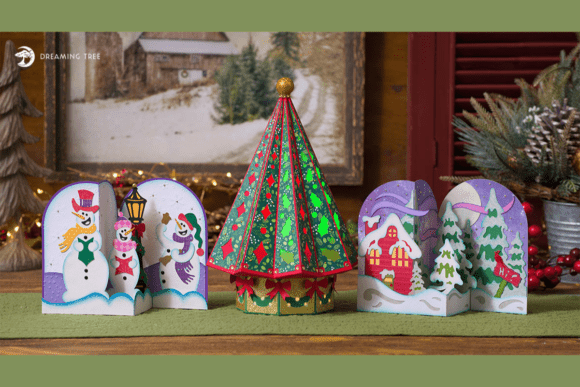
Early Bird Christmas SVG Bundle
Encontrar los elementos de diseño adecuados puede ser un desafío, pero Early Bird Christmas SVG Bundle ofrece una colección excepcional que eleva tu trabajo al instante.
Elaborado con precisión, Early Bird Christmas SVG Bundle proporciona vectores limpios, tipografía suave y una licencia comercial para tu tranquilidad.